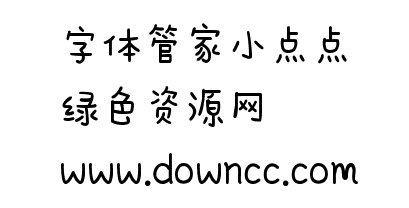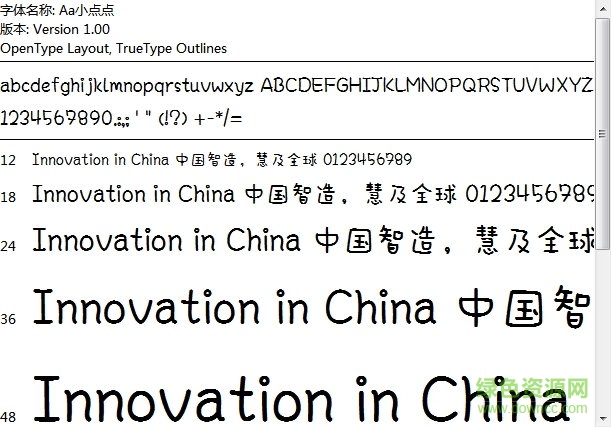
字體管家小點(diǎn)點(diǎn)是一款十分Q萌可愛的卡通字體,結(jié)構(gòu)寬窄隨意看起來卻十分和諧,字跡清晰醒目有著極佳的辨識(shí)度,給你的設(shè)計(jì)增添了個(gè)性色彩,綠色資源網(wǎng)今日推薦!
元?dú)馍倥⌒↑c(diǎn)來啦!超人氣漫畫形象丁小點(diǎn)字體,字體結(jié)構(gòu)以丁小點(diǎn)的五官表情為元素,字形活潑,仿佛一個(gè)元?dú)鉂M滿的少女躍然紙上。
字體管家小點(diǎn)點(diǎn),也叫作Aa小點(diǎn)點(diǎn)字體,是aa字體管家平臺(tái)推出的一款個(gè)性手寫字體, 商用請(qǐng)聯(lián)系【字體管家】作者授權(quán),字庫完整,能滿足設(shè)計(jì)師們的各種需求,為你的平面設(shè)計(jì)、包裝設(shè)計(jì)帶來不錯(cuò)的效果!